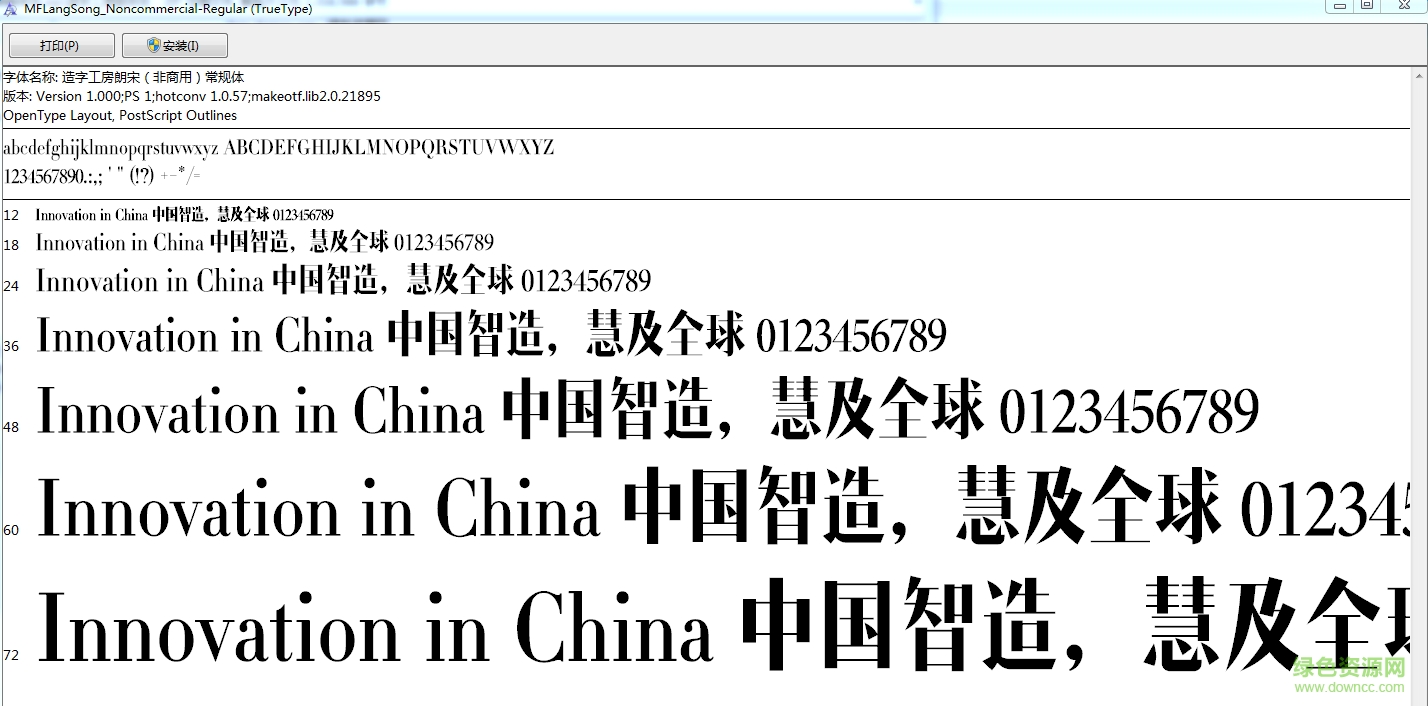
造字工房朗宋(非商用)常規(guī)體
造字工房朗宋體是一款造字工房類簡潔穩(wěn)重風(fēng)格字體軟件,朗宋體給人非常沉穩(wěn)有力的感覺,適用于各大廣告標(biāo)題設(shè)計,也深受廣大書法家的喜愛,還有更多好看字體盡情期待,歡迎到綠色資源網(wǎng)下載體驗!
字體介紹
造字工房朗宋體是一款應(yīng)用于設(shè)計方面的簡體中文字體,整體字形筆畫簡潔有力,筆畫粗細(xì)關(guān)系明確,使得字形空間結(jié)構(gòu)自然平衡,整套字體莊、重嚴(yán)謹(jǐn),沉穩(wěn)厚重,適用于文字標(biāo)題、廣告設(shè)計等等視覺環(huán)境,有著極強的應(yīng)用空間。